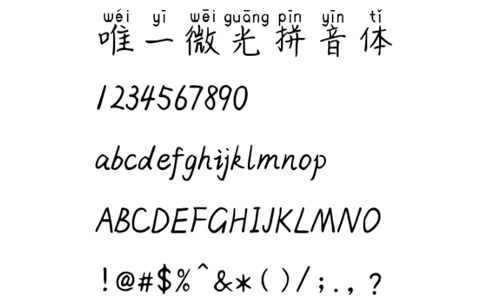
唯一微光拼音體字體是一款自帶拼音標(biāo)注效果的中文藝術(shù)字體,該字體第一眼看上去非常的瀟灑俊逸、自然舒展、賞心悅目,歡迎大家前來下載。
薔薇盛放的年華盡端,你微笑的剪影,是守望靜謐的唯一微光。——唯一微光拼音體。
本字體是在國家標(biāo)準(zhǔn)簡體字庫GB2312所包含6763漢字的基礎(chǔ)上,又增加了近200常用字,已經(jīng)覆蓋了大陸99.75%的漢字使用頻率,足以滿足日常需求。